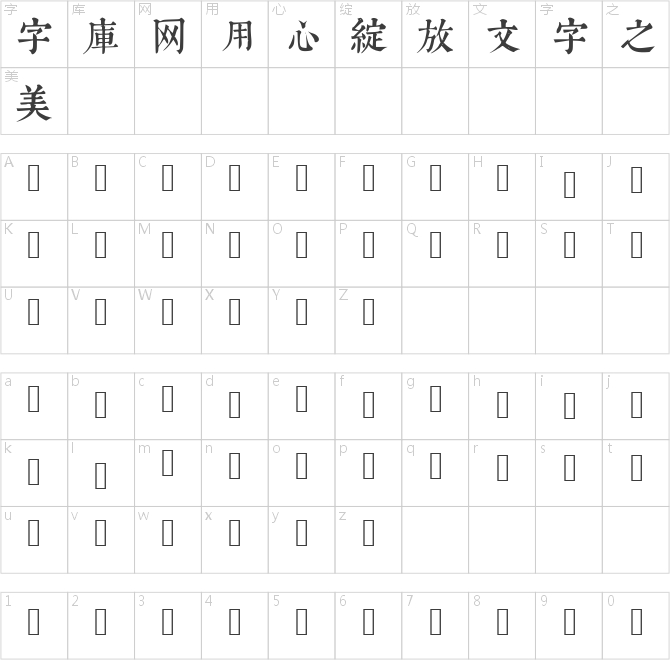
字体名称: 康熙字典体常用
康熙字典体常用版
收字7000 个
字體資料
我们推出的字体版本是电脑从七千多页的《康熙字典武英殿版本》自动化切割字头制作而成的。
我们仔细的计算了康熙字头字收,总收字是47403个,虽借用电脑的自动切割可省下好多时间,但也要人工手动去翻七千多页的《康熙字典武英殿版本》作字头与古文筛选及删掉多馀的字头图片,流程大致如下:
1)系统自动OCR版面切割并取出每一页面的字头图片
2)手动把多馀的字头图片删掉
3)手动定义古文字头
4)系统自动排序字头图片
5)加入字序/Unicode
6)完成后即可点按字头图片取得文本内容及制作康熙字体等古籍数字化工作
关于收字范围,常用版收字有约9000字,扣除因简转繁的重复字后有约7000个康熙字,收字主要参考《规范汉字表》及《繁体常用字表》,同时收字是在CJK基本汉字集內。
通用版收字约19000字,扣除因简转繁的重复字后有约17000个康熙字,主要在常用版收字之外再参考《繁体字次常用字表》及CJK基本汉字集內的康熙字。
完整版收字约49000字,扣除因简转繁的重复字后是47043个康熙字,也就是康熙字头的完整收字。其实康熙字头也有约80多个重复字,康熙字体采用Unicode 15 字集,没有使用造字。康熙字典收字和Unicode 的编码是有少许不同之处及争议的,尤其在Unicode 收字原则、异体字等方面,无论如何目前康熙字典采用Unicode做编码及数字化仍是最佳的选